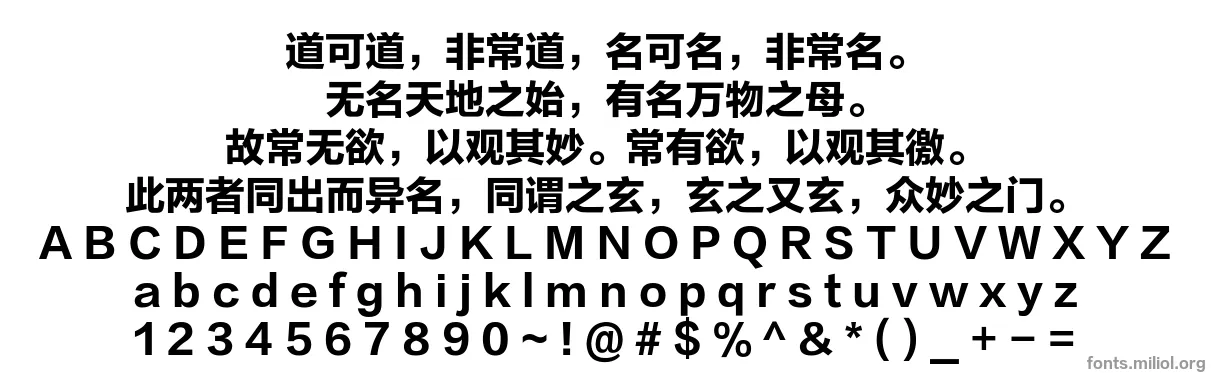
**方正兰亭大黑_GBK字体简介**
方正兰亭大黑_GBK(FZLanTingHei-EB-GBK)是方正字库推出的一款现代黑体字体,属于兰亭黑系列的加粗版本。其设计风格简洁有力,笔画粗壮均匀,结构严谨,兼具视觉冲击力与良好的可读性,适合标题、广告、品牌标识等需要突出强调的场合。
该字体采用GBK编码标准,支持繁简体中文及多种符号,兼容性广泛,可满足印刷、数字媒体等多场景需求。其文件名标注为FZLTDHK--GBK1-0,是方正字库中的经典商用字体之一。